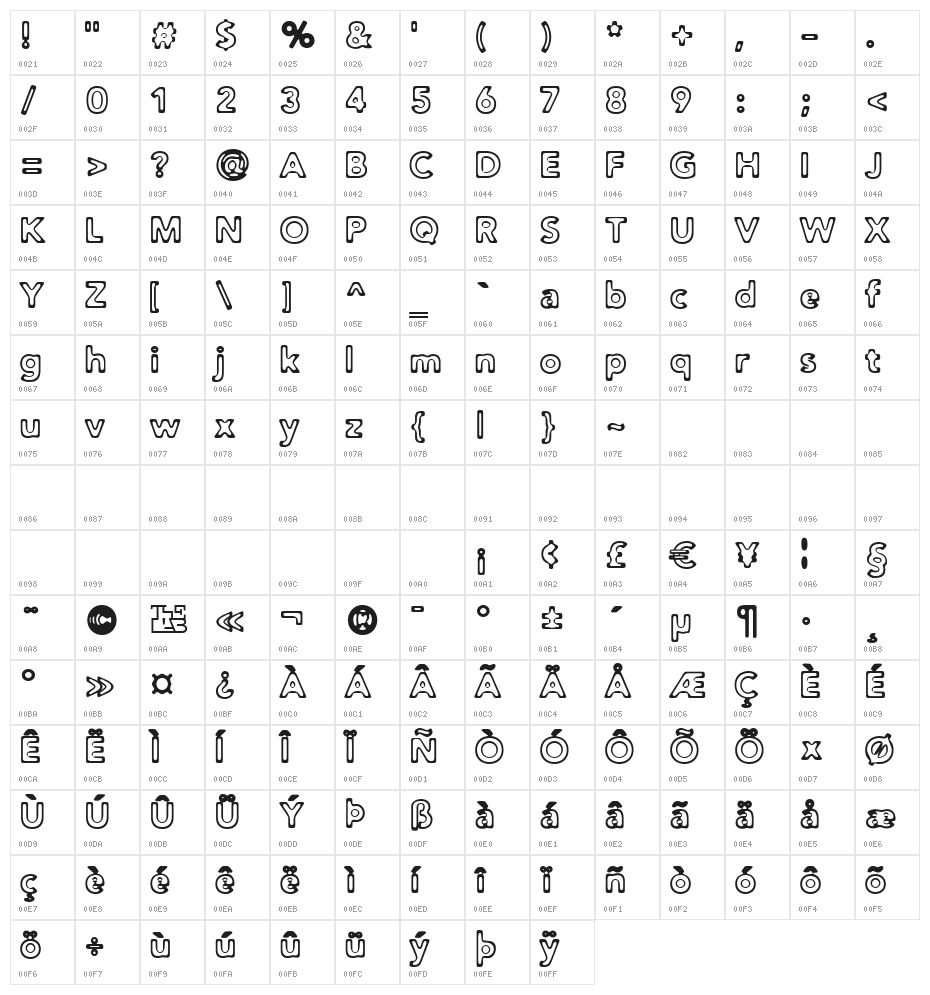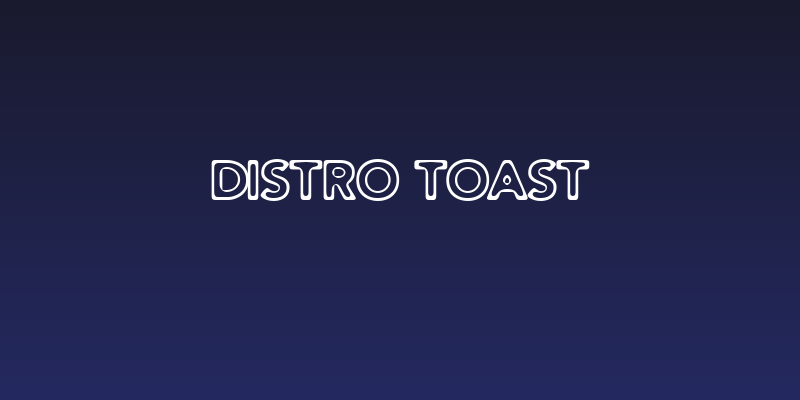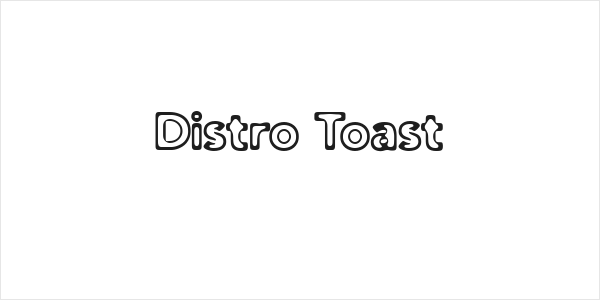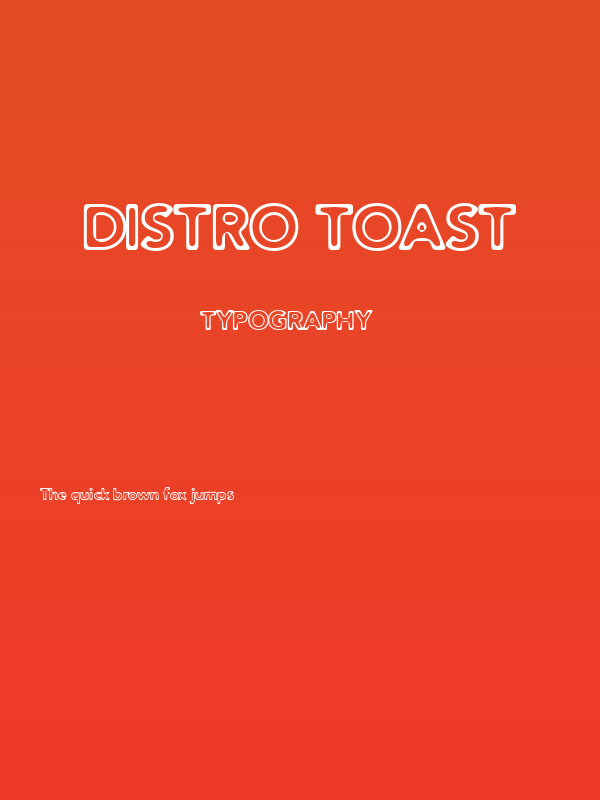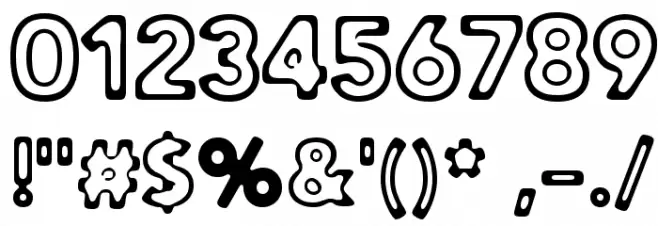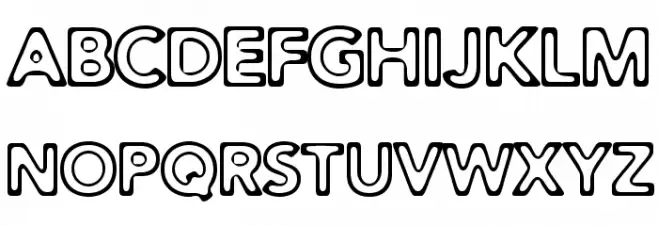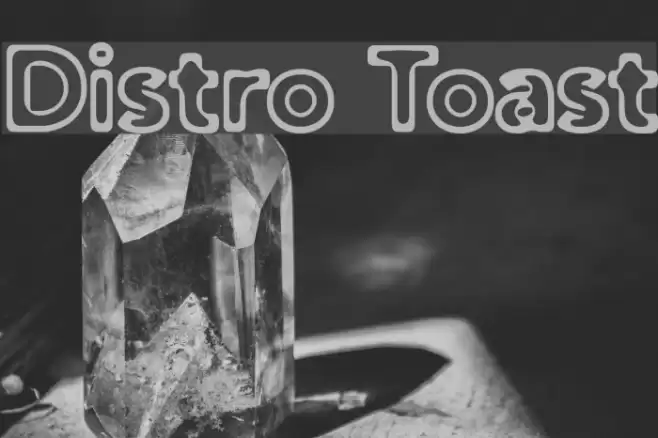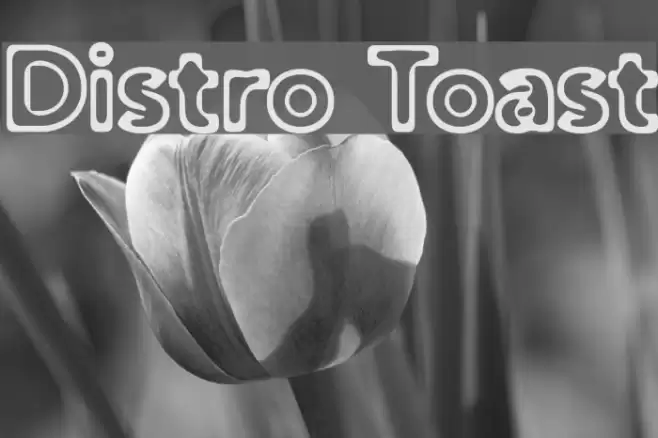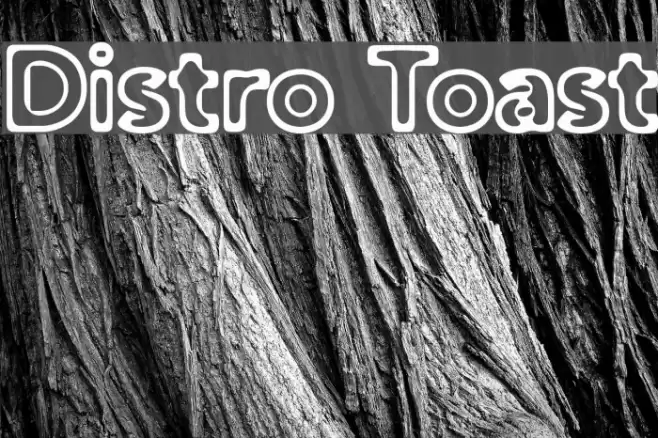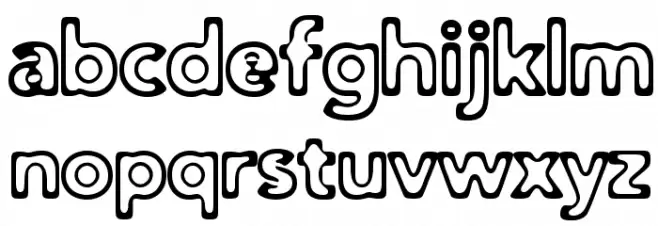
Distro Toast Font
Fonts by Apostrophic Lab
| Gesamtstil | Playful, Modern |
| Vorgeschlagene Projekte | Ideal for children's books, playful branding, posters, and creative digital content. |